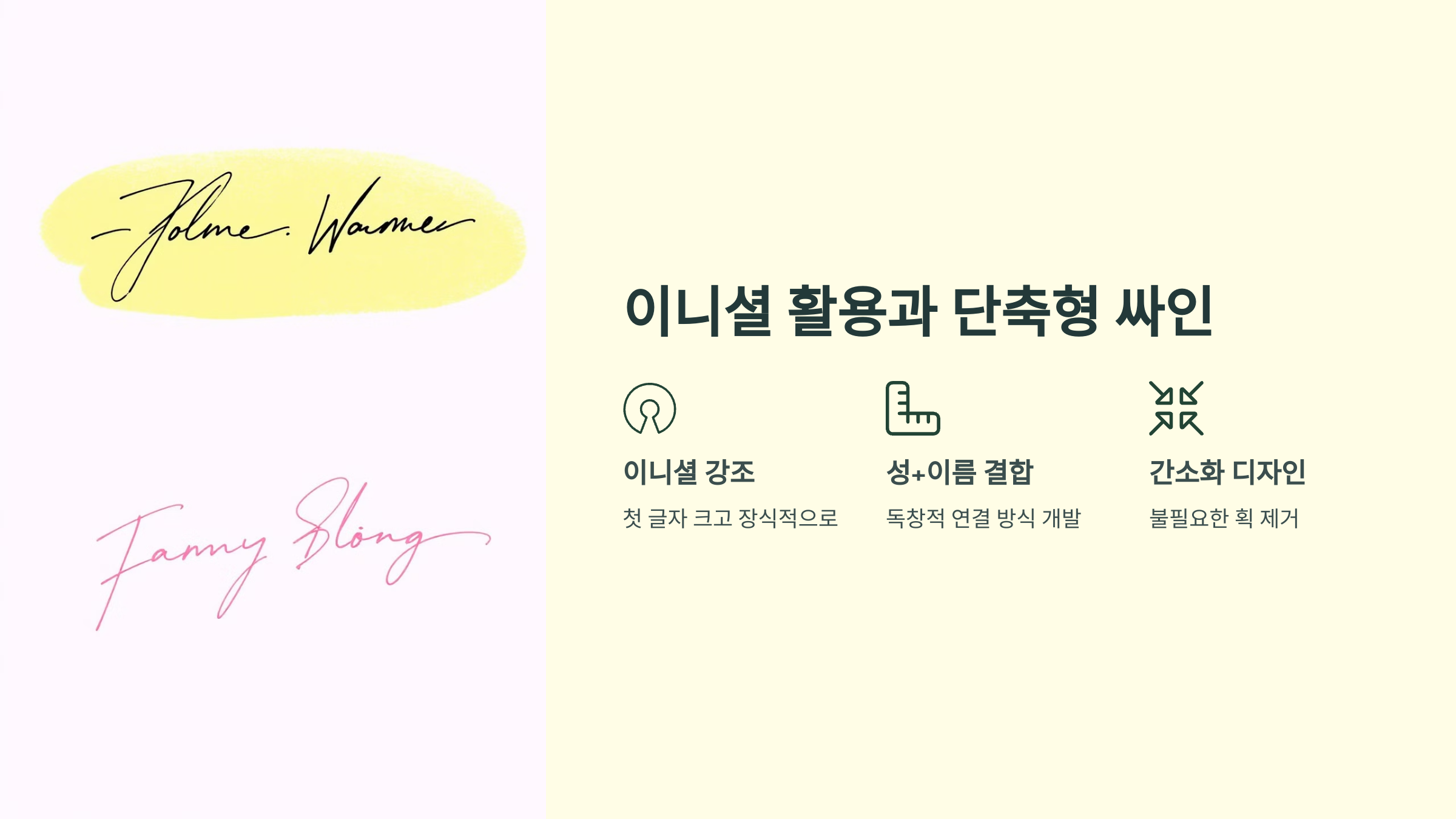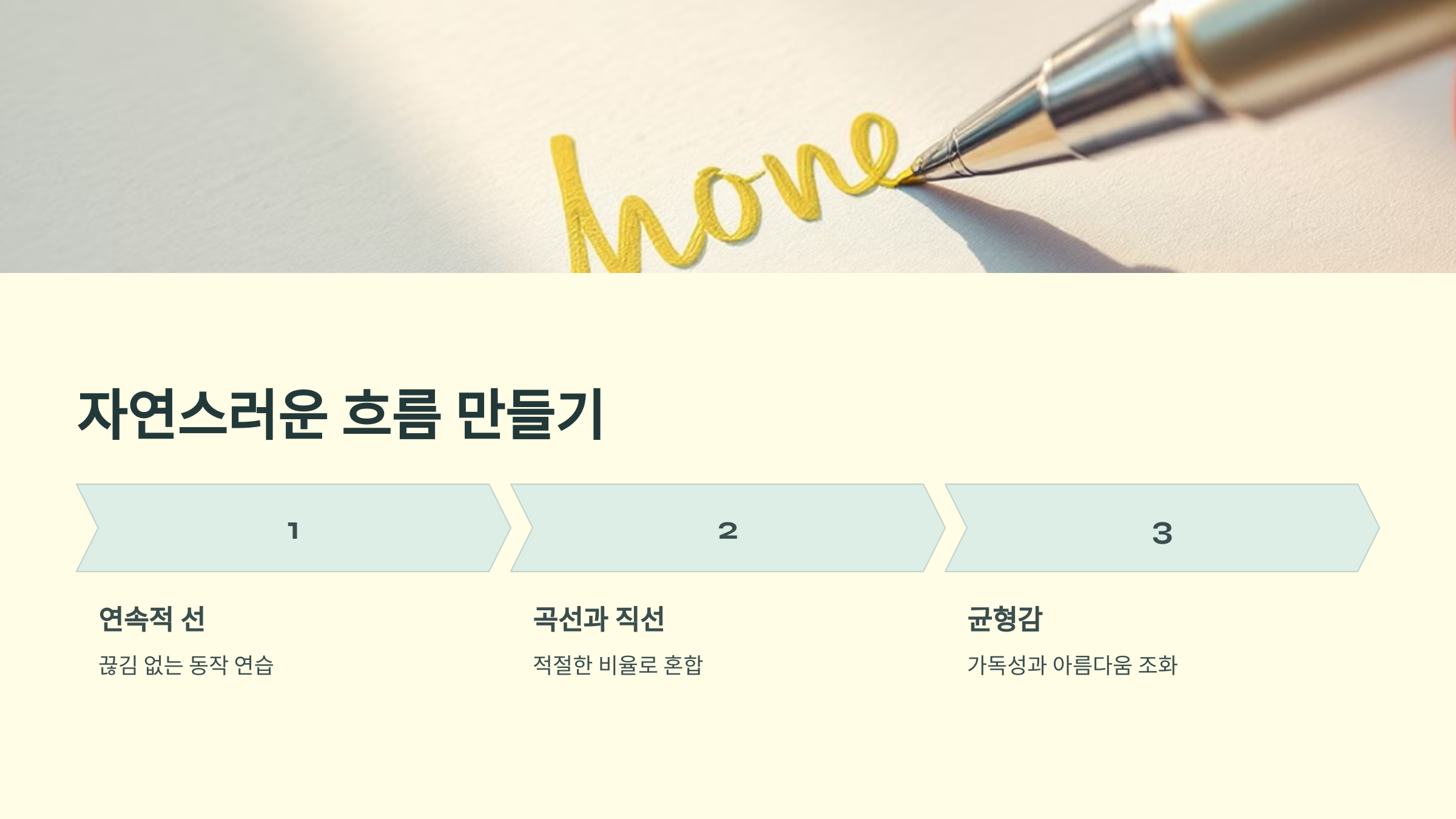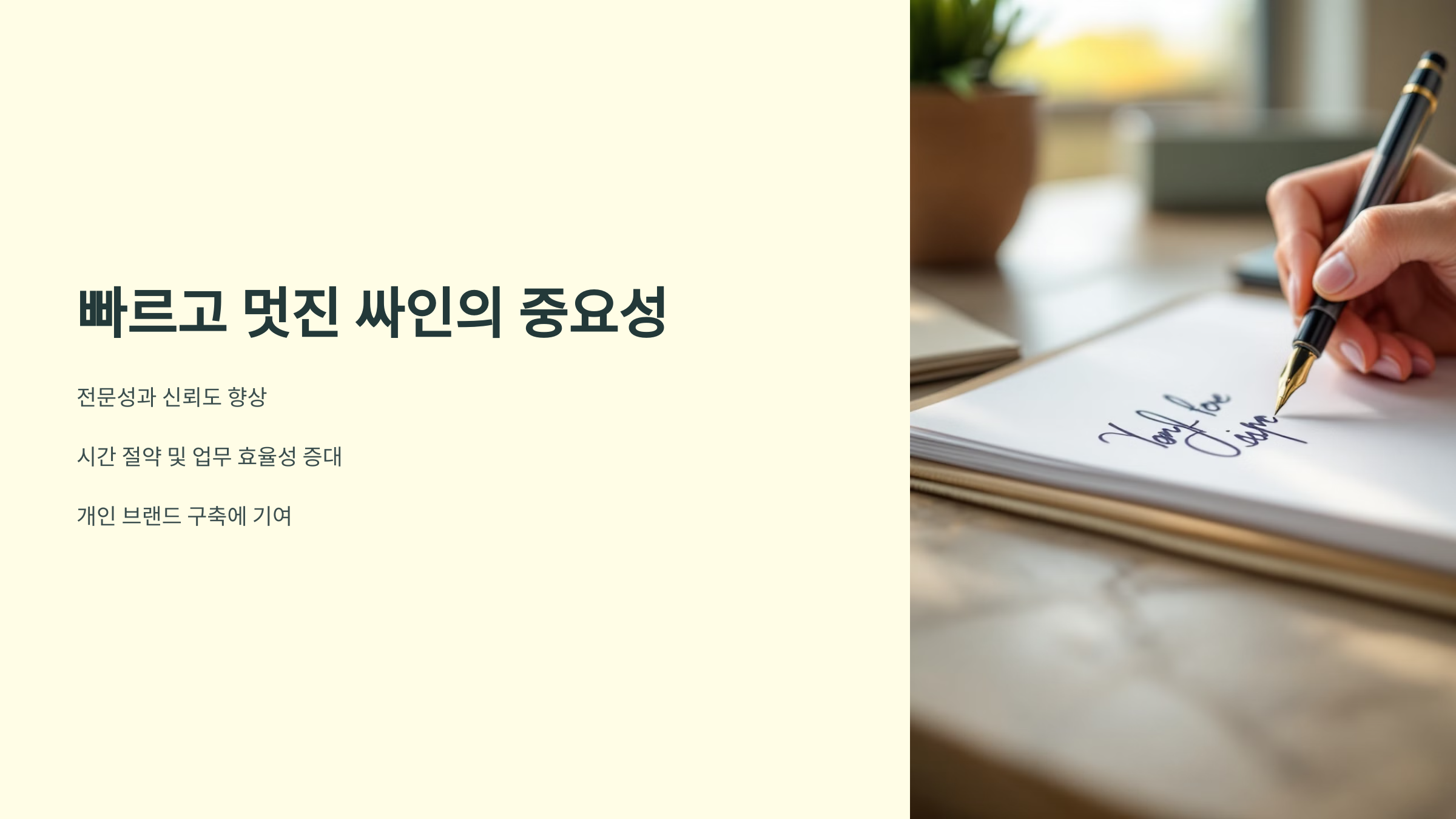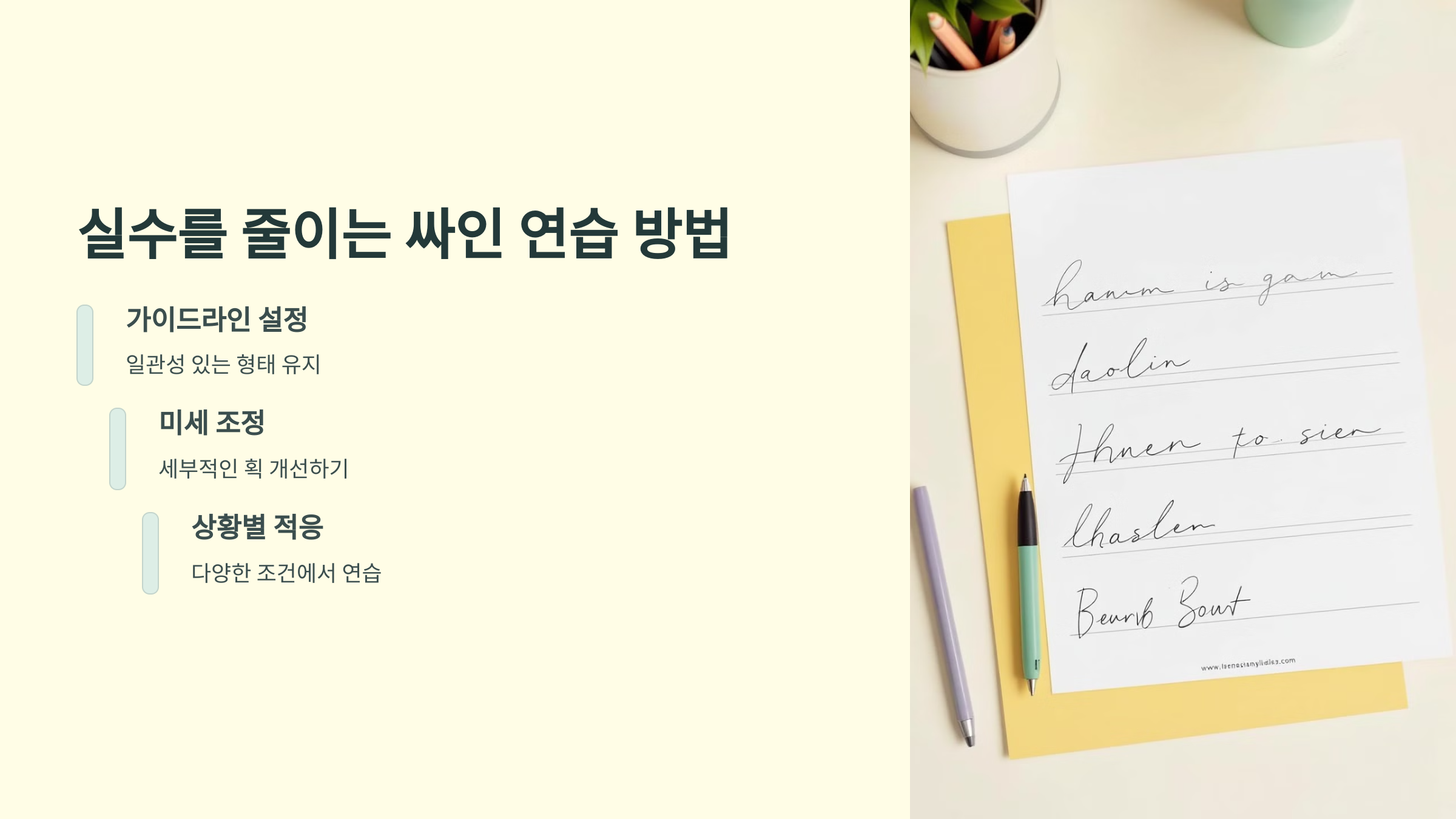
싸인을 빠르고 멋지게 쓰는 것은 비즈니스, 계약, 서류 작업에서 매우 중요한 요소예요. 너무 오래 걸리면 실용성이 떨어지고, 너무 대충 쓰면 멋이 없겠죠? 그래서 빠르면서도 스타일을 유지하는 싸인을 연습하는 것이 필요해요! ⚡
그럼 먼저, 빠르고 멋진 싸인이 중요한 이유부터 알아볼까요? 🖋️
빠르고 멋진 싸인의 중요성 ⚡
빠르고 멋진 싸인은 개인 브랜딩, 신뢰감, 효율성을 높이는 역할을 해요. 특히 비즈니스, 계약서, 서류 작성에서 너무 오래 걸리거나 흐트러진 싸인은 비효율적이죠. 🖋️
하지만 속도만 빠르다고 좋은 게 아니에요. 가독성과 스타일을 유지하면서도 자연스럽게 싸인을 할 수 있어야 해요! ✅
📌 빠르고 멋진 싸인이 필요한 이유 🎯
이유 설명 1. 실용성 계약서, 영수증 등에서 빠르게 작성할 수 있음 2. 신뢰감 서명할 때 흔들림이 없으면 더 신뢰감을 줌 3. 개성 표현 스타일리시한 싸인은 본인의 아이덴티티를 나타냄 4. 보안성 빠르면서도 독창적인 싸인은 위조하기 어려움 이제 빠르고 멋진 싸인을 위해 손의 컨트롤과 필압 조절하는 방법을 배워볼까요? ✍️
손의 컨트롤과 필압 조절 ✋🖊️
빠르고 멋진 싸인을 하려면 손의 움직임을 자연스럽게 컨트롤하고, 필압(펜을 누르는 힘)을 조절하는 것이 중요해요. 너무 힘을 주면 손이 금방 피로해지고, 너무 힘을 빼면 흐릿한 싸인이 나올 수 있어요. ⚖️
📌 손의 컨트롤과 필압 조절법 ✅
방법 설명 1. 손목을 부드럽게 사용 손목을 너무 고정하지 말고 자연스럽게 움직여야 함 2. 필압을 일정하게 유지 강약 조절을 하되, 한 번에 너무 세게 누르지 않기 3. 손가락 힘 최소화 손가락보다는 손목과 팔의 힘으로 싸인하기 4. 속도 조절 처음엔 천천히, 점점 빠르게 연습하기 손의 컨트롤이 좋아지면 싸인의 흐름이 더욱 자연스러워져요! 그럼 이제, 자연스럽게 흐름을 만들면서 싸인하는 방법을 알아볼까요? 🔄
자연스러운 흐름 만들기 🔄
싸인을 빠르게 하면서도 멋스럽게 만들려면 자연스러운 흐름(flow)이 중요해요. 글자가 끊기거나 어색하게 멈추면 싸인이 부자연스러워 보일 수 있어요. ✍️
📌 자연스러운 싸인 흐름을 위한 4가지 원칙 ✅
원칙 설명 1. 획을 끊지 않기 글자 간 연결을 부드럽게 해 싸인이 자연스럽게 이어지도록 하기 2. 곡선 활용 직선적인 글자라도 살짝 곡선을 넣어 부드러운 느낌을 주기 3. 속도 리듬 유지 처음부터 끝까지 일정한 리듬으로 싸인하기 4. 마지막 마무리 강조 싸인의 끝부분에 길게 늘이는 효과나 포인트 추가 이제 싸인을 더 빠르게 하기 위해 이니셜 활용과 단축형 싸인을 알아볼까요? 🔤
이니셜 활용과 단축형 싸인 🔤
싸인을 빠르게 하면서도 멋스럽게 만들려면 이니셜을 활용하거나 단축형 스타일을 적용하는 게 좋아요. 이름을 길게 쓰는 대신 핵심 요소만 남기고 변형하면 속도를 높이면서도 개성을 유지할 수 있어요. ✍️
📌 이니셜 활용 및 단축형 싸인 스타일 ✅
스타일 설명 예시 1. 성 + 이니셜 성을 적고 이름은 첫 글자만 사용 "Kim J." / "Choi S." 2. 이니셜 조합 이름과 성의 첫 글자만 사용하여 짧고 간결하게 "J.K." / "S.L." 3. 필기체 변형 이니셜을 필기체로 변형하여 개성 추가 "Jk" / "Sl" 4. 기호 활용 점, 별, 밑줄 등을 추가해 독창적인 느낌 "M.Lee ✨" / "S.Lim —" 이니셜과 단축형 싸인을 활용하면 빠르면서도 세련된 싸인을 만들 수 있어요! 그럼 이제, 속도감 있는 싸인을 연습하는 방법을 배워볼까요? 🚀
속도감 있는 싸인 연습법 🚀
싸인을 빠르고 멋지게 쓰려면 속도감 있는 연습이 필수예요! 처음에는 천천히 연습하고, 점점 속도를 높이는 방식으로 연습해야 해요. 🖊️
📌 속도감 있는 싸인을 연습하는 4가지 방법 ✅
연습 방법 설명 1. 같은 싸인 100번 반복 종이에 같은 싸인을 반복해서 연습하며 속도를 올리기 2. 타이머 설정 제한 시간을 정하고 빠르게 싸인 연습하기 3. 다양한 필기구 사용 볼펜, 만년필 등 다양한 도구로 연습해 필기감 익히기 4. 공중 싸인 연습 손목의 유연성을 기르기 위해 공중에서 싸인 연습하기 이렇게 연습하면 빠르고 자연스러운 싸인을 완성할 수 있어요! 그럼 이제, 싸인할 때 실수를 줄이는 방법을 알아볼까요? ⛔
실수를 줄이는 싸인 연습 방법 ⛔
싸인을 빠르고 멋지게 쓰면서도 실수를 줄이는 것이 중요해요. 특히 계약서, 공식 문서에서 실수하면 수정이 어렵기 때문에 안정적인 싸인을 연습해야 해요. ✍️
📌 싸인 실수를 줄이는 4가지 연습법 ✅
연습법 설명 1. 천천히 연습 후 속도 올리기 처음엔 정확성을 높이고, 이후 속도를 조절하며 연습 2. 종이 여러 장 사용하기 한 장에 여러 번 연습하지 말고 새로운 종이에 반복 연습 3. 싸인 영상 촬영하기 손 움직임을 녹화하여 실수를 파악하고 교정 4. 계약서 연습 실제 서류 크기에 맞춰 연습해 실전 감각 익히기 이제 싸인 실수를 줄이면서도 멋진 스타일을 유지할 수 있어요! 마지막으로, 싸인과 관련된 자주 묻는 질문(FAQ)을 정리해 볼게요. 📢
FAQ
Q1. 싸인을 더 빠르게 하려면 어떻게 연습해야 하나요?
A1. 처음엔 천천히 연습한 후 점점 속도를 올리는 방식이 좋아요. 손목과 손가락을 유연하게 풀어주면 속도감 있는 싸인을 만들 수 있어요. 💨
Q2. 싸인할 때 가장 많이 하는 실수는?
A2. 획이 끊기거나 글자 간격이 불균형한 경우가 많아요. 처음엔 천천히 연습하면서 균형을 잡는 것이 중요해요! ⚖️
Q3. 싸인을 바꿔도 되나요?
A3. 공식 문서에서 사용하는 싸인은 일관성을 유지하는 것이 좋아요. 하지만 개인적으로는 스타일을 바꿔가며 여러 번 연습해 볼 수 있어요. ✍️
Q4. 싸인을 빠르게 하면 필압이 너무 강해져요. 어떻게 해야 하나요?
A4. 손가락 힘을 줄이고 손목과 팔을 활용하는 것이 중요해요. 손의 긴장을 풀고 연습하면 부드럽고 빠른 싸인을 만들 수 있어요. ✨
Q5. 싸인을 연습할 때 어떤 필기구를 사용하는 게 좋나요?
A5. 볼펜, 만년필, 연필 등 다양한 필기구로 연습해보세요. 싸인 스타일에 따라 적절한 필기구를 선택하는 것이 좋아요. 🖊️
Q6. 싸인을 더 멋지게 보이게 하는 방법이 있나요?
A6. 이니셜을 강조하거나, 곡선과 직선을 조합하는 것이 좋아요. 또한, 특수 기호(밑줄, 점, 별 등)를 추가하면 더욱 멋져 보여요! ⭐
Q7. 디지털 싸인과 손글씨 싸인은 어떤 차이가 있나요?
A7. 디지털 싸인은 태블릿이나 스마트폰에서 생성하는 전자 서명이고, 손글씨 싸인은 종이에 직접 작성하는 아날로그 방식이에요. 공식적인 문서에서는 전자 서명이 점점 더 많이 활용되고 있어요! 📱
Q8. 싸인의 법적 효력은 무엇인가요?
A8. 계약서나 공식 문서에서 사용하는 싸인은 법적으로 중요한 역할을 해요. 따라서 일관된 싸인을 유지하는 것이 중요해요. ⚖️